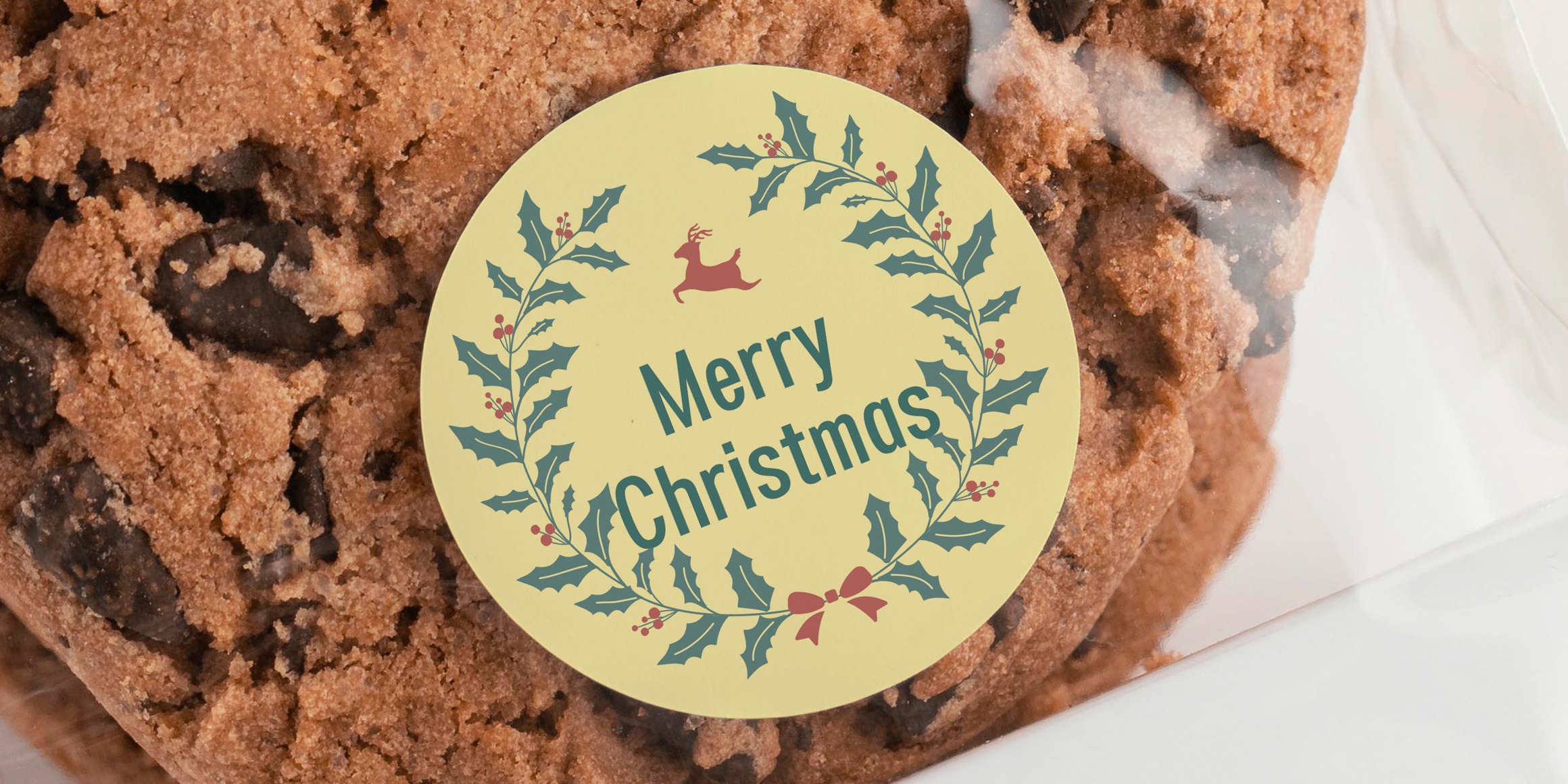
HGTallGGothicssi Pro
HG키큰꼬딕씨는 극단적인 장체의 구조가 특징인 제목용 고딕 서체입니다. 꼬딕씨시리즈이기 때문에 꽉 찬 네모꼴 서체에서 출발하였으며, 자폭이 극단적으로 좁은 서체이기 때문에 특수한 상황에서 필요한 서체입니다. 디자인적인 요소를 최소화하여 모던하게 디자인하였고, Grid 위에서 초성과 중성의 간격을 일정하게 유지하여 규칙성 있는 서체로 디자인되었습니다.
5가지 웨이트와 획 대비가 있는 Contrast 폰트로 총 6 스타일로 패밀리가 구성되어 있어 용도에 맞게 사용할 수 있으며, 2,350자의 한글 글립이 디자인되어 있습니다. 한글의 본질적 구조의 문제 속에서 공간에 대한 고민을 통해 필요한 부분에서 가변폭으로 디자인되었습니다. 영문 디자인은 한글의 특징을 그대로 접목하는 방향으로 디자인되었습니다.
- Kim dongkwan
- 한글 2,350자 / 라틴 95자 / 약물 985자
- HG키큰꼬딕씨 / HGTallGGothicssi Pro